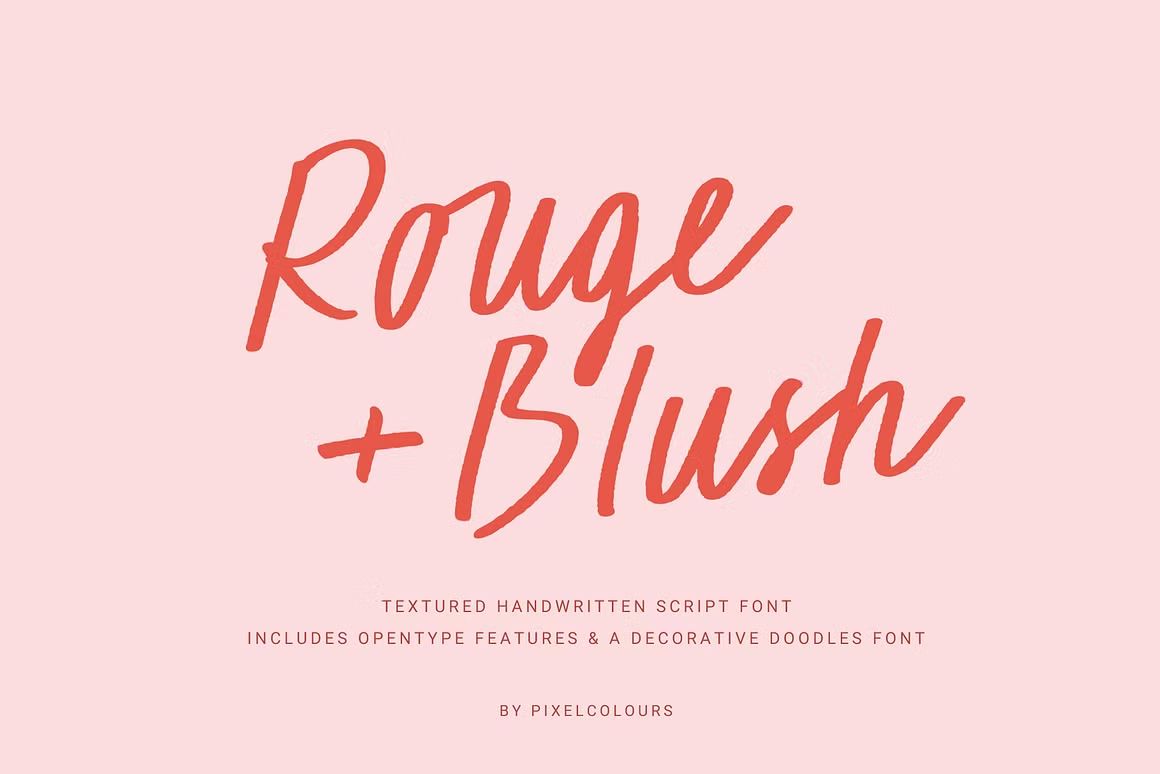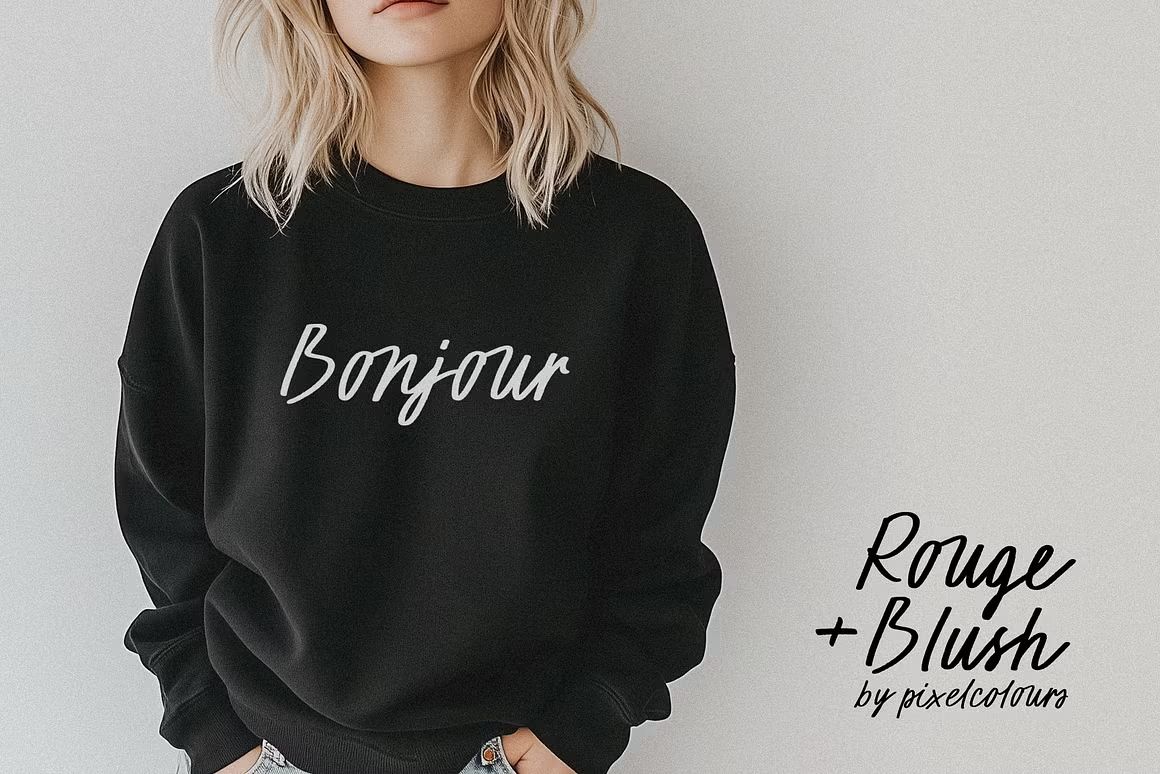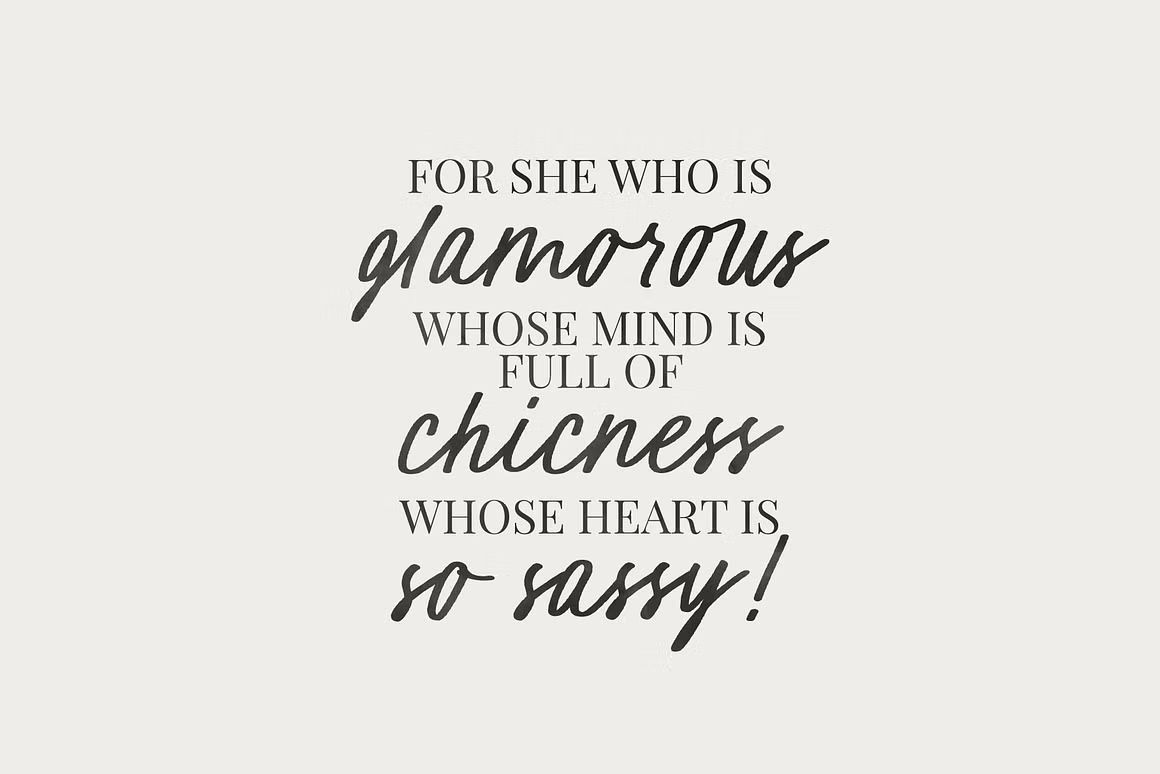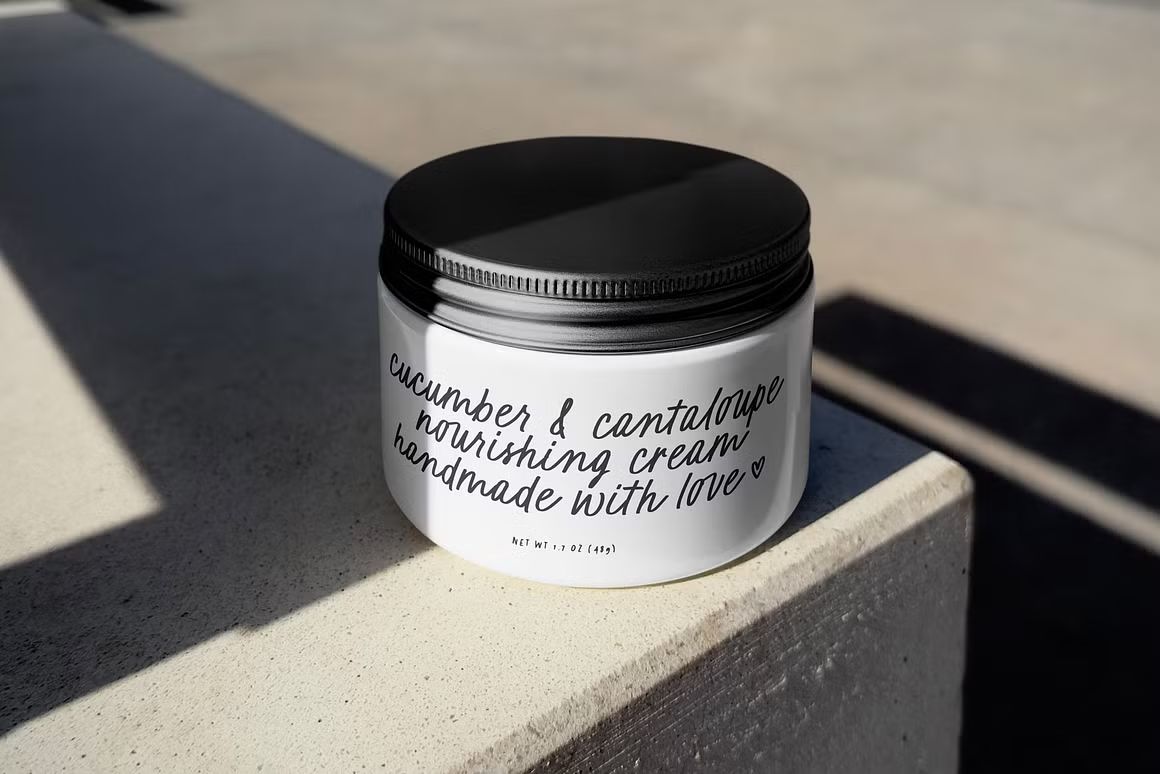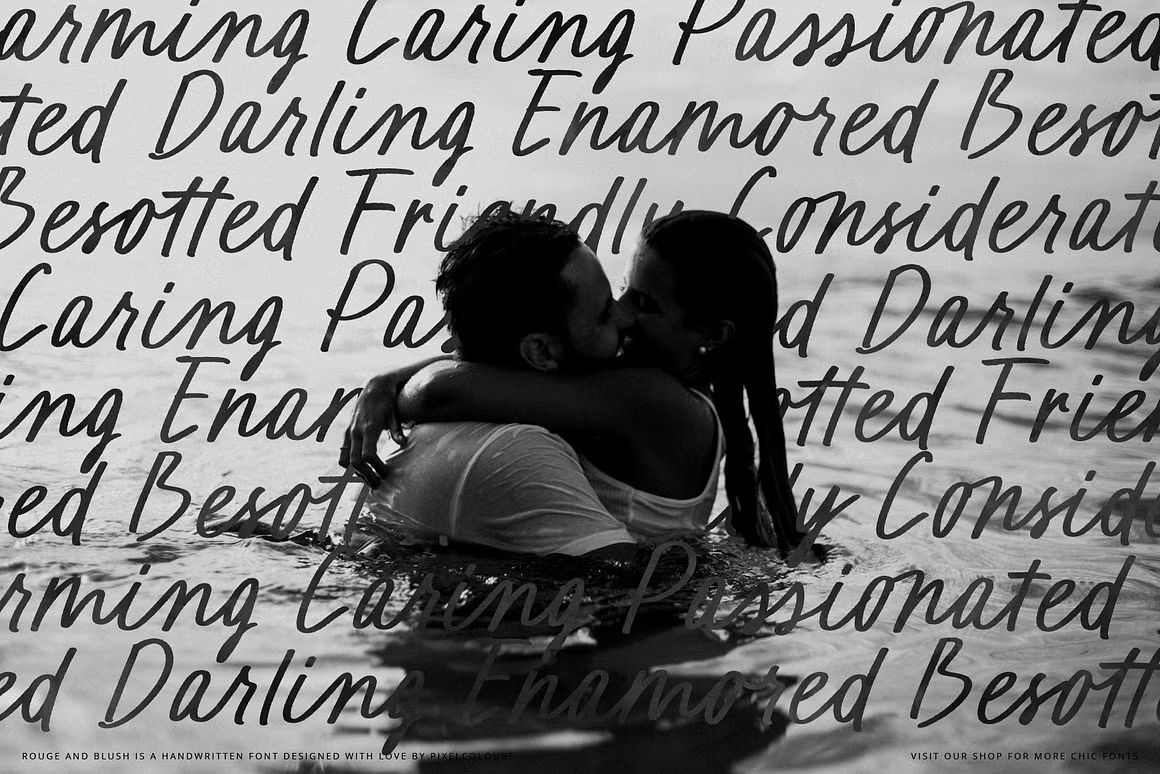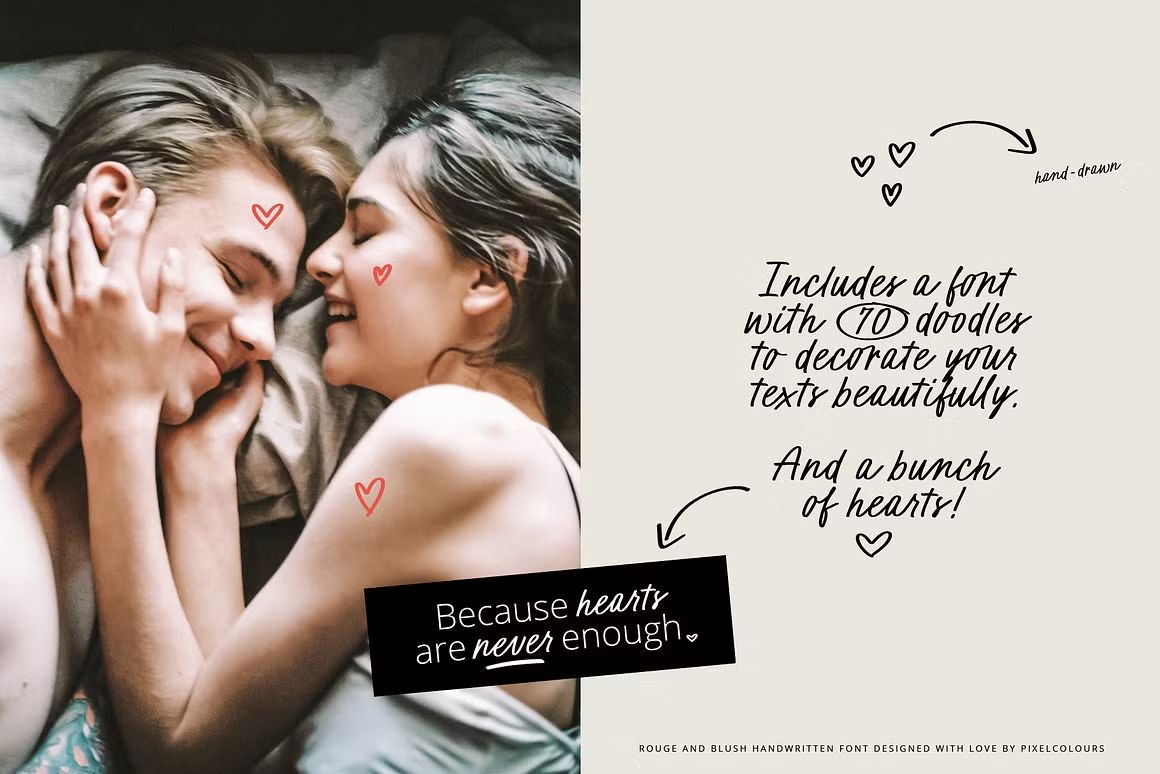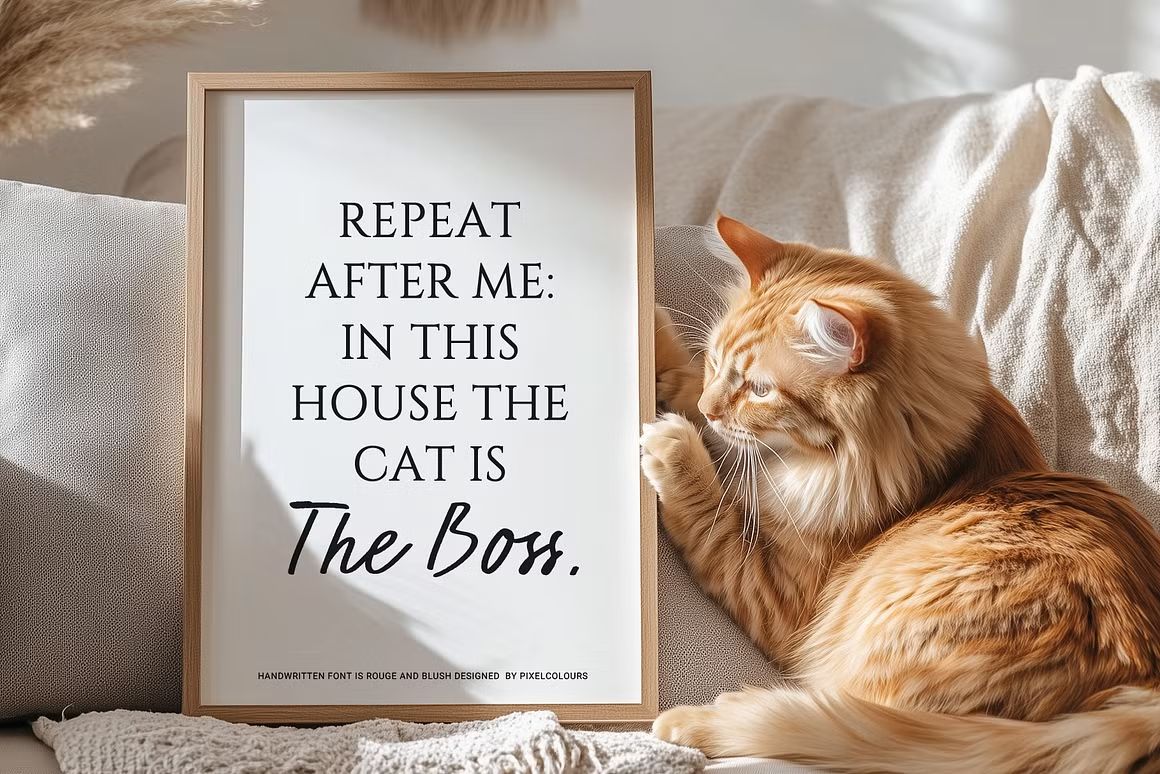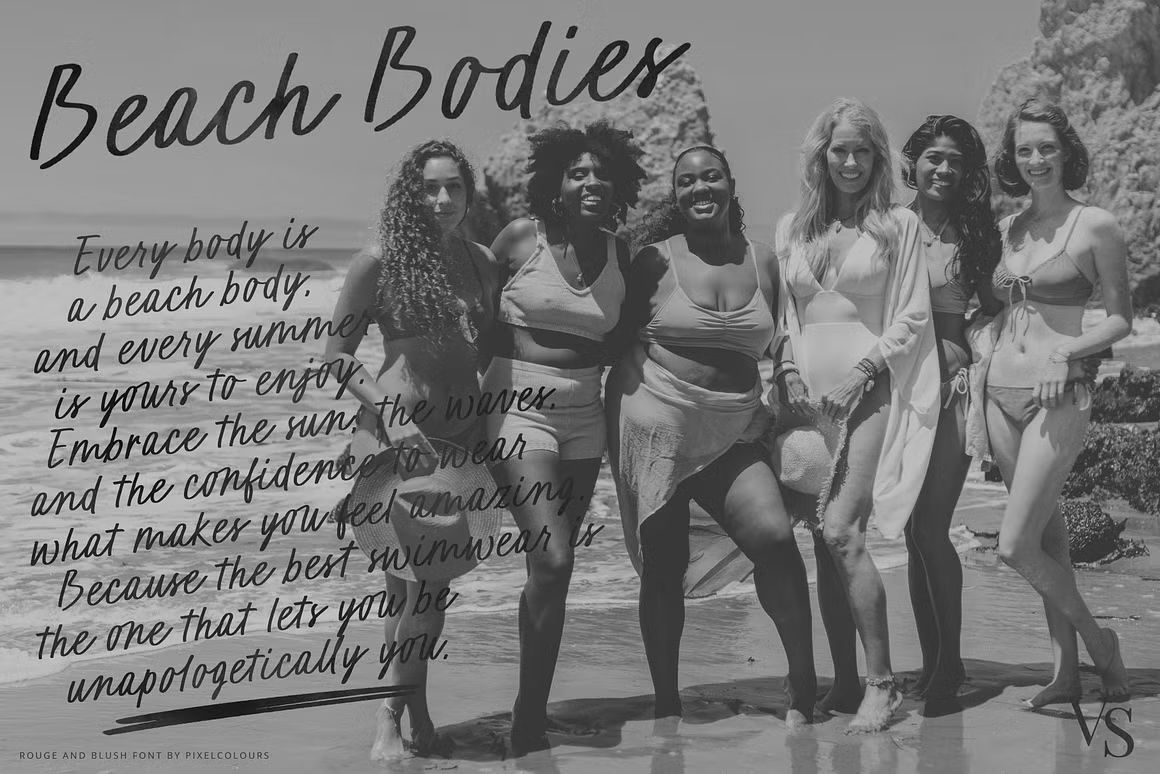
Rouge +Blush – Script Font
Rouge +Blush adalah font script lembut dan romantis, cocok untuk wedding, branding feminin, dan desain estetik. Format OTF/TTF/WOFF, siap digunakan.
Rouge +Blush adalah font script bergaya feminin dan romantis, dengan goresan tangan yang lembut, elegan, dan mengalir. Didesain untuk memberikan kesan manis dan anggun, font ini sangat cocok untuk undangan pernikahan, logo brand kecantikan, kutipan estetik, kemasan produk, dan konten media sosial bertema soft & chic.
• Script font dengan gaya tulisan tangan feminin
• Ideal untuk wedding, beauty brand, dan desain romantis
• Termasuk huruf besar, kecil, angka, simbol, dan ligatur